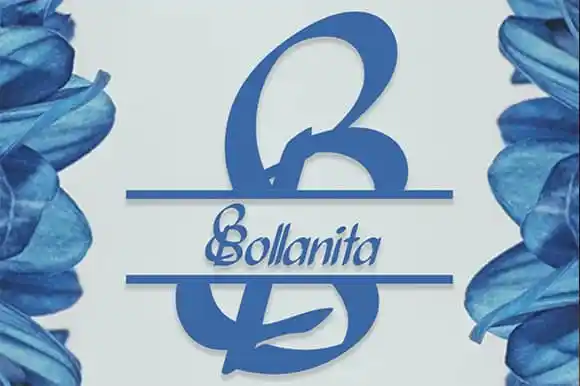
A Bollanita Calligraphy Font é uma peça elegante e sofisticada para quem busca deixar seus projetos inesquecíveis. Desenvolvida por andikastudio, esta fonte chama a atenção por sua perfeição na criação de letras em estilo calligrafia, ideal para diversos usos. A Bollanita é perfeitamente adequada tanto para ambientes visuais tradicionais como para plataformas digitais. Suas linhas finas e delicadas tornam-a perfeita para uso em wall displays ou embalagens de produtos, criando um ar elegante e sofisticado. Além disso, seu design é ideal para criações que exijam uma escrita à mão, desde invitations até a estaçãoária. Para designers gráficos que buscam expressar seus projetos com uma paleta de letras únicas e sutis, a Bollanita é um investimento que valoriza seu trabalho. Com este fonte em mãos, você pode garantir que suas criações se destacam, tanto offline quanto online. Seja para personalizar sua próxima peça de arte digital ou criar embalagens exclusivas, a Bollanita Calligraphy Font estará sempre pronta para ajudá-lo a alcançar um resultado excepcional.